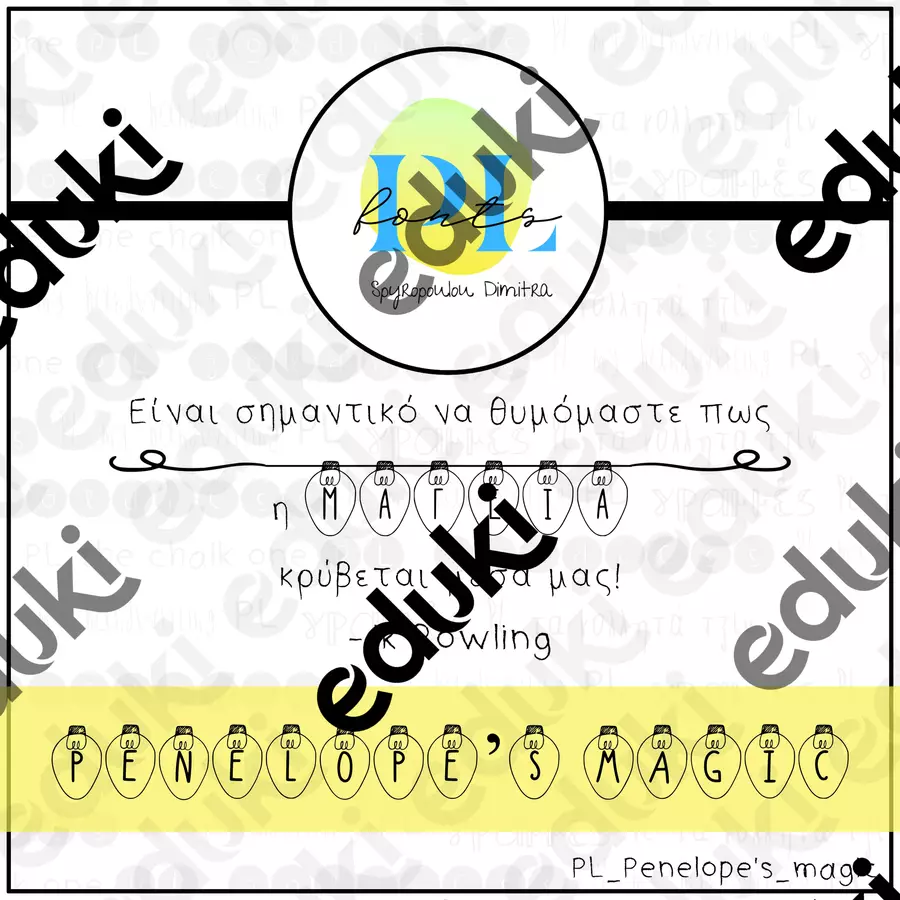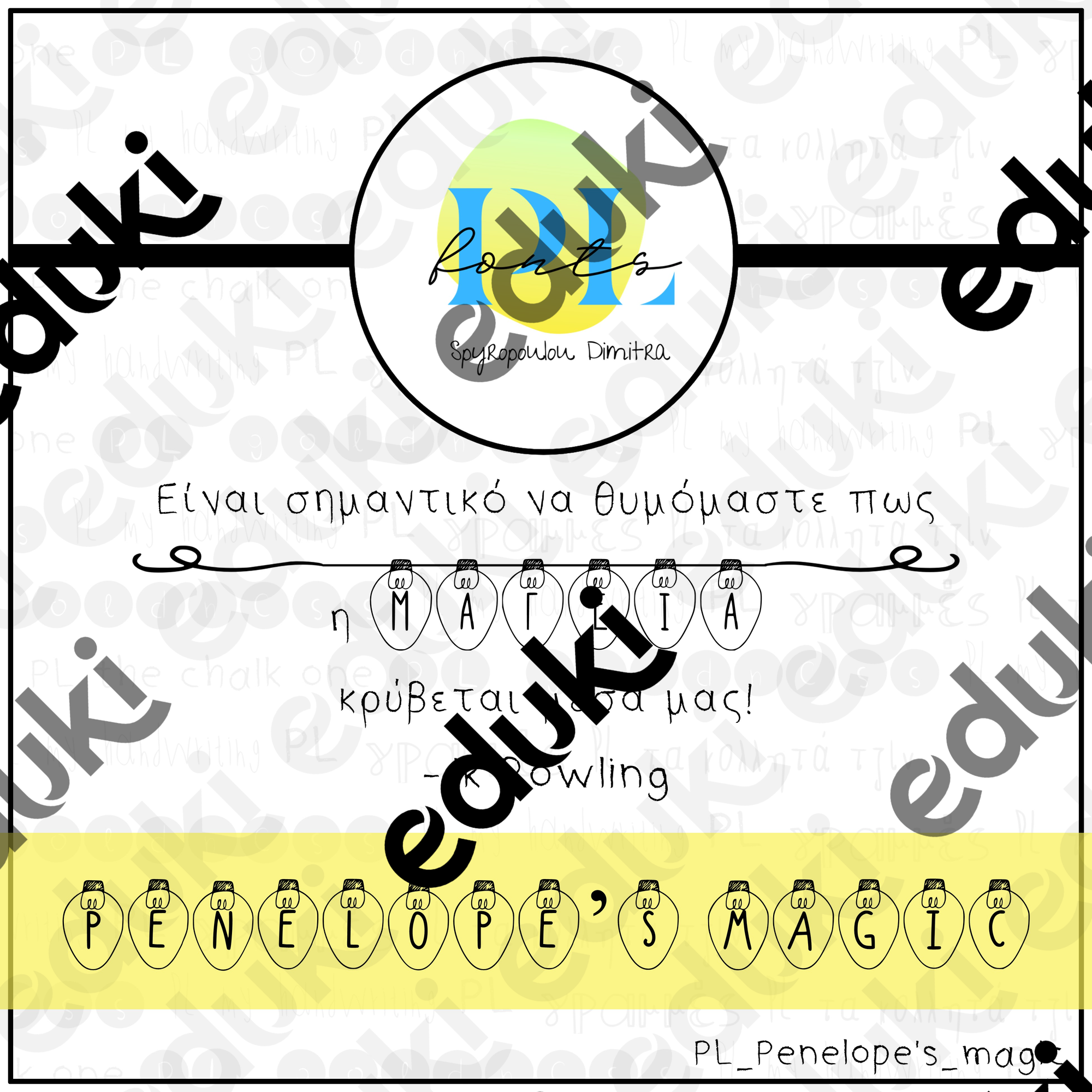
Αυτή η γραμματοσειρά είναι αφιερωμένη στην υπέροχη Πηνελόπη, την blogger της "Τάξη Μαγική". Η στήριξη, η πίστη της σε εμένα ήταν η έμπνευση για αυτή τη γραμματοσειρά.
Ονομάζεται "Penelope's magic" (H μαγεία της Πηνελόπης) και αποτελεί γραμματοσειρά τίτλων (script font). Είναι γράμματα τοποθετημένα μέσα σε φωτάκια, γιατί έτσι φωτίζει η Πηνελόπη τη δική μου ζωή.
Επίσης παντώντας το σύμβολο "\" στο πληκτορολόγιο σας βγαίνει ένα κενό φωτάκι. Μπορεί να το μεγεθύνετε και μέσα να προσθέσετε εικόνες ή φωτογραφίες.
Η γραμματοσειρά περιλαμβάνει ελληνικούς χαρακτήρες καθώς και αγγλικούς, αριθμούς, μαθηματικά σύμβολα και σημεία στίξης.
- CLIPART ΜΕ ΓΡΑΜΜΕΣ, εάν θέλετε τα φωτάκια να μοιάζει πως είναι σε γιρλάντα, όπως είναι στην παρουσίαση που βλέπετε πιο πάνω.
This font is devoted to Penelope, blogger of "Taxi Magiki". Her support and faith in me were the inspiration I was looking for to create this font.
It's called "Penelope's magic" and it's a script font, great for titles, not text. The letters are written inside lightbulbs, 'cause Penelope is lighting up my whole life.
Moreover, when pressing the "\" button on your keyboard, a blank lightbulb will be seen. You can enlarge it and fill it with pictures or icons.
This font includes Greek characters as well as English ones, numbers, mathematical symbols, and punctuation marks.
- CLIPART WITH LINES so that you can create your own garland with lights as I did in the presentation of the font.